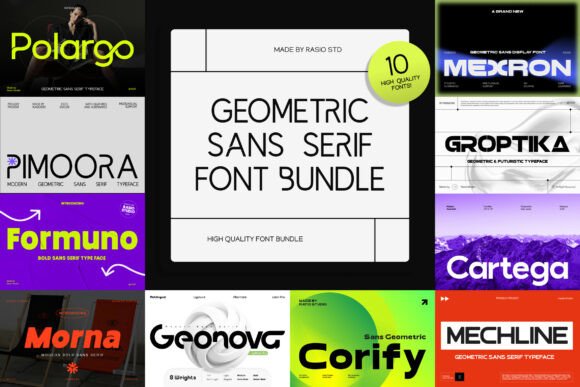
Geometric Sans Serif Bundle
Trouver les bons éléments de conception peut être un défi, mais Geometric Sans Serif Bundle propose une collection exceptionnelle qui rehausse instantanément votre travail.